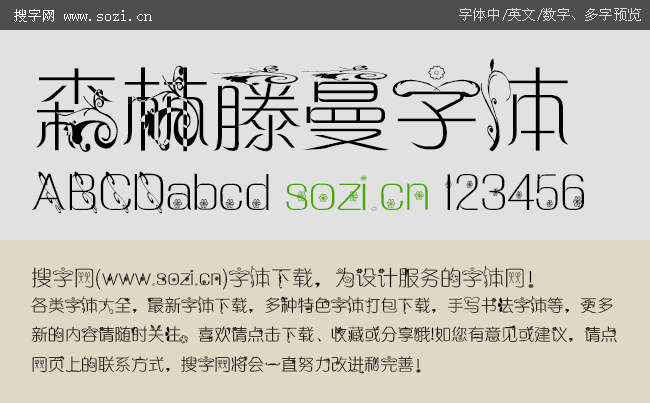
森林藤蔓字體
搜字網(wǎng)給大家提供一款很有趣的手機(jī)中文字體下載。修改者給他起名為森林藤蔓字體,這款手機(jī)字體是將中倩體字體部分筆畫替換成了漂亮的花紋圖案。中倩體筆劃粗細(xì)對(duì)比適中,婉轉(zhuǎn)嫵媚,溫順乖巧,看似平淡無(wú)奇,卻能給人以美的感受。
插入花紋后增加了趣味性,是一款非常可愛(ài)的卡通字體,特別適合喜歡手機(jī)字體個(gè)性一些的朋友在手機(jī)上安裝使用。